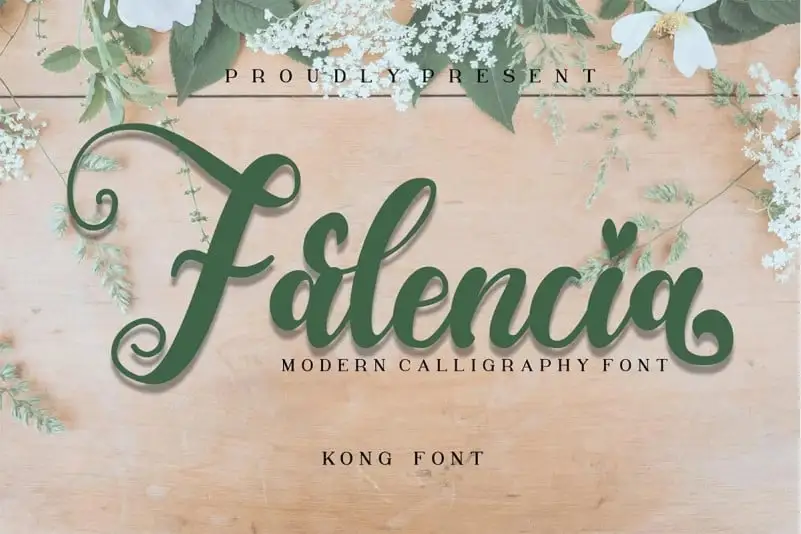
Falencia Script Font – Fonte Grátis
Falencia Script Font
Falencia Script é uma fonte script moderna criada por Kong Font, perfeita para adicionar um toque elegante às criações digitais. Seja ela a escolha ideal para convites de casamento, cartões de agradecimento, citações e cartazes personalizados; logotipos, cartões de visita, marcações e embalagens de produtos; chás de boda, sacolas shopping, camisetas customizadas; capas de livros ou cartões de convite, qualquer design que exija um toque de letra escrita a mão irá beneficiar do seu uso. Seja para eventos especiais ou designs no dia-a-dia, Falencia Script trará sofisticação e delicadeza a qualquer projeto gráfico.